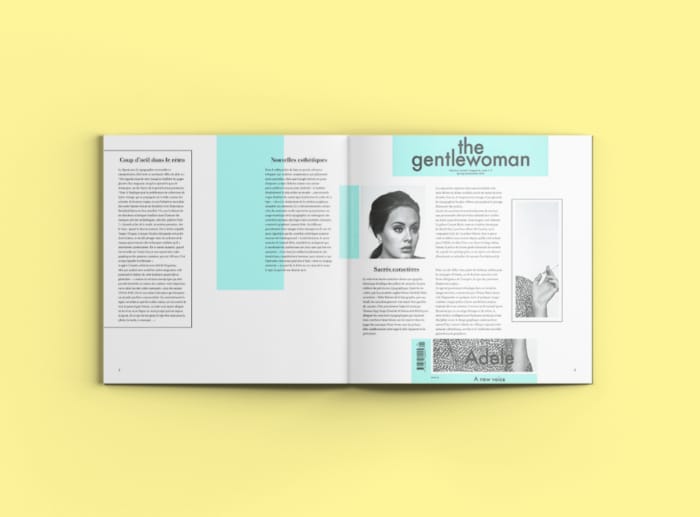
5 règles à suivre pour associer parfaitement vos polices d’écriture
Les polices d’écriture jouent un rôle crucial dans votre charte graphique. Que ce soit sur votre site internet ou vos supports écrits, elles doivent attirer et garder l’attention des lecteurs ! Leur rôle est également de transmettre une image cohérente avec les valeurs de votre entreprise.
Une bonne association des polices d’écriture crée de l’harmonie, de la fluidité et surtout de la cohérence dans votre design.
Si vous voulez donner un aspect plus professionnel à votre ligne graphique, voici 5 règles à respecter pour réussir l’association des typographies !
En multipliant les polices sur votre site, vous risquez de créer de la confusion chez vos visiteurs, tout en entravant la lisibilité de vos contenus. Voilà pourquoi il est recommandé de se limiter à 3 polices de caractère différentes, grand maximum.
Il vous faut ainsi adopter une police qui :
Cependant, la typographie utilisée pour les appels à l’action peut être la même que vos titres. Ce n’est qu’une option supplémentaire qui dépend de votre créativité, de votre activité et de votre charte graphique globale.
Les polices de même famille aident à créer une hiérarchie, tout en garantissant une cohérence visuelle. C’est le moyen le plus facile d’associer des typographies avec goût.
Parmi les familles les plus connues, nous avons :
Servez-vous de la chronologie pour trouver des polices complémentaires. En effet, chaque époque a connu ses tendances ! Généralement, elles s’accordent parfaitement entre elles.
Par exemple, vous pouvez combiner les typographies Garaldes, qui datent de la Haute-Renaissance et dont les plus connues sont Garamond, Sabon ou encore Bembo.
Vous aimez le style baroque de Times New Roman ? Les polices de la même époque sont Baskerville et Perpetua.
L’association de vos polices doit être équilibrée. Tout d’abord, elles doivent se compléter. Ce qui signifie que même si elles ne se ressemblent pas, elles doivent offrir une hiérarchie visuelle aux visiteurs et aux lecteurs.
Une bonne façon d’y parvenir est de combiner une police avec empattement et une autre sans empattement. Cette association populaire est souvent utilisée dans les projets graphiques destinés à l’impression. Pour les écrans, vous pouvez vous contenter des caractères sans empattement.
Vous pouvez aussi utiliser une police d’en-tête au caractère marqué (fantaisiste, manuscrite, géométrique…), puis l’équilibrer avec un corps de texte neutre.
Associer des polices permet d’établir une hiérarchie dans vos contenus. Mais simplement augmenter la taille de vos titres ne sera pas suffisant pour créer une harmonie.
Pour différencier vos titres du contenu, il vous faudra également jouer sur :
Créer un contraste visible entre les polices améliore l’ergonomie, la lecture et toute l’expérience utilisateur. N’oubliez pas que les visiteurs doivent immédiatement distinguer les phrases fortes ou les titres, des textes secondaires.
Pour rendre l’expérience utilisateur agréable, pensez à tester vos typographies. Que ce soit avec un vrai texte ou un générateur « Lorem Ipsum ». Vous pourrez visualiser en direct la cohérence des polices d’écriture sélectionnées.